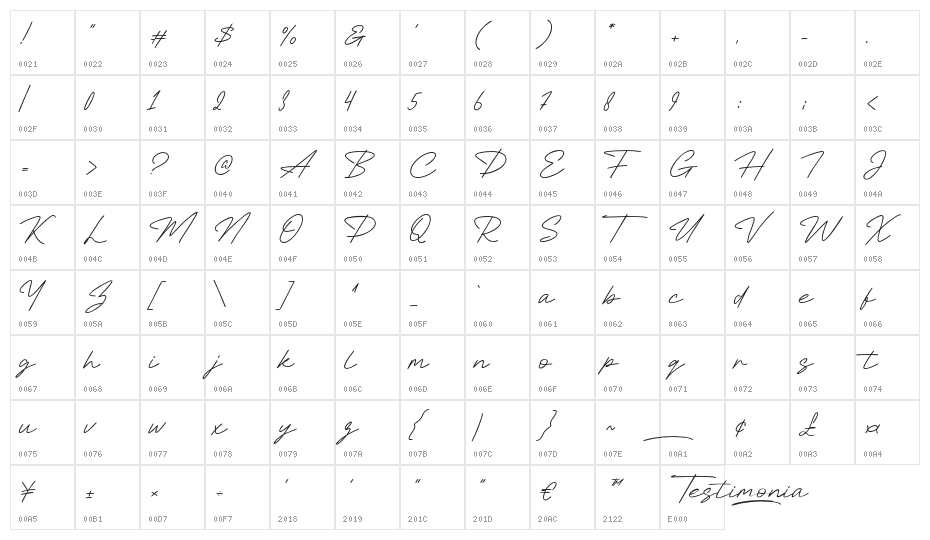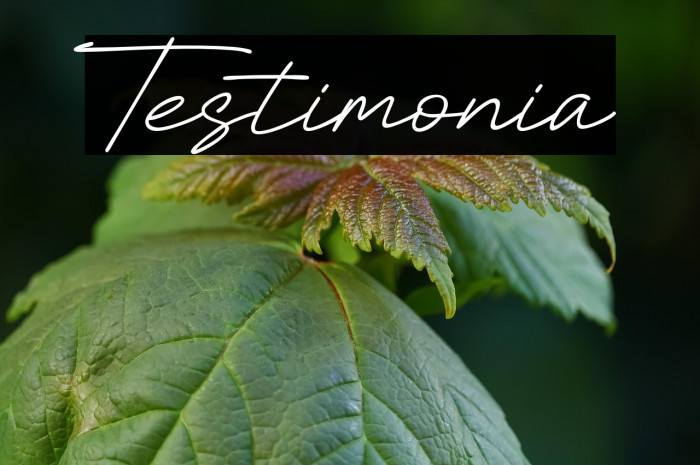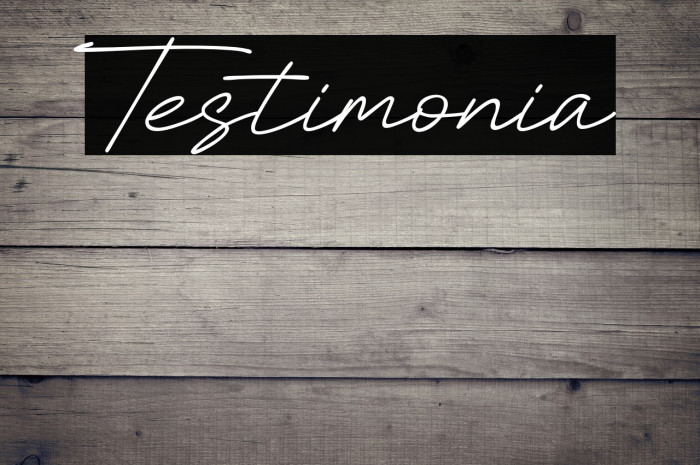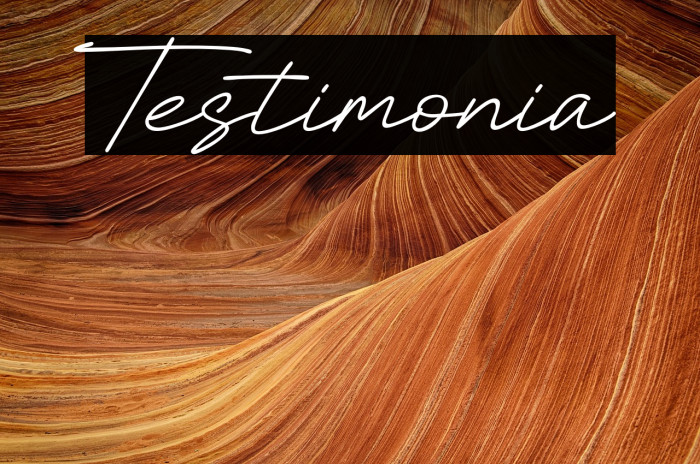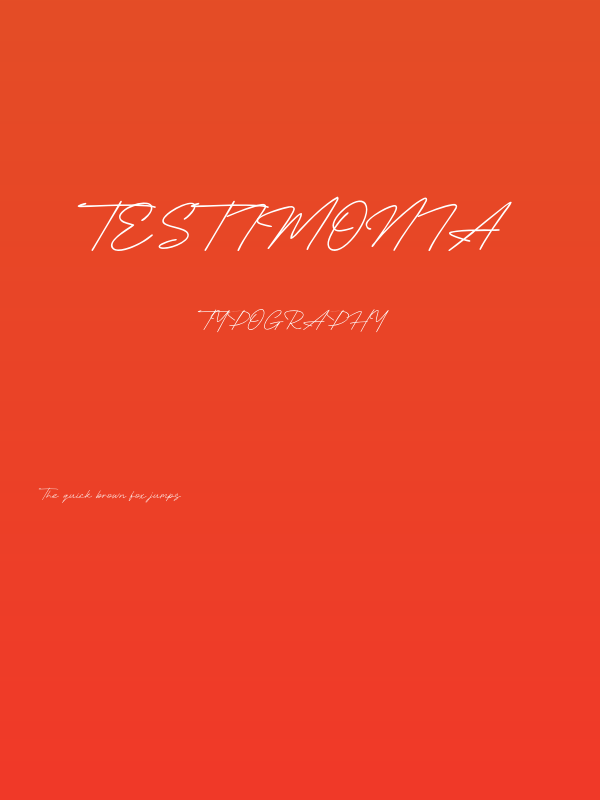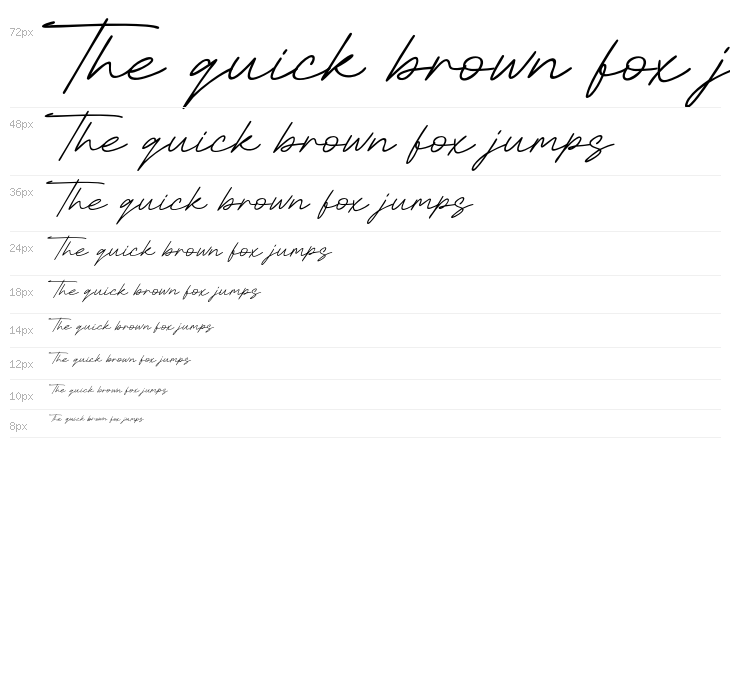
Testimonia Font
| Stil general | Elegant, Artistic |
| Caz de utilizare | Logos, Invitations, Personal Branding |
| Proiecte propuse | Ideal for wedding invitations, personal branding, greeting cards, and artistic projects. |